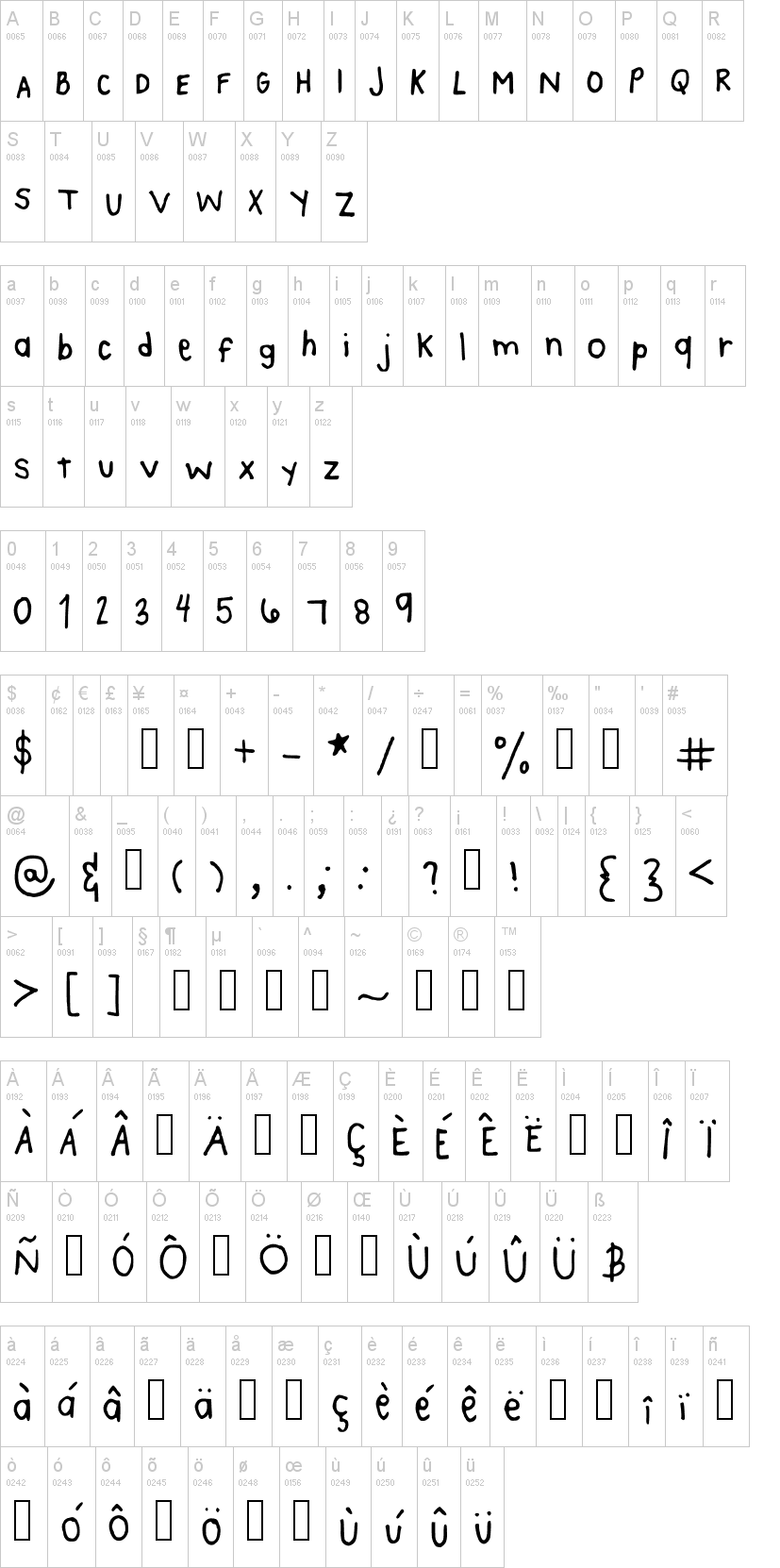
Kaes Handwriting 是一款由美国设计师Kae Fonts设计的手写字体。该字体有着温暖、活泼、清新的外表,可以用于各种设计项目,如书籍封面、海报、品牌标识等。该字体的字形具有细腻的线条,可以创造出轻松、自然的效果,适合用于各种文字设计,尤其是那些需要轻松、活泼的气氛的设计。内容介绍
Kaes Handwriting是一款非常不错的手写艺术字体,具有很好的视觉感,适合于文化类的宣传设计、商业类品牌的广告和产品包装设计以及个性化文字排版等较多场景。